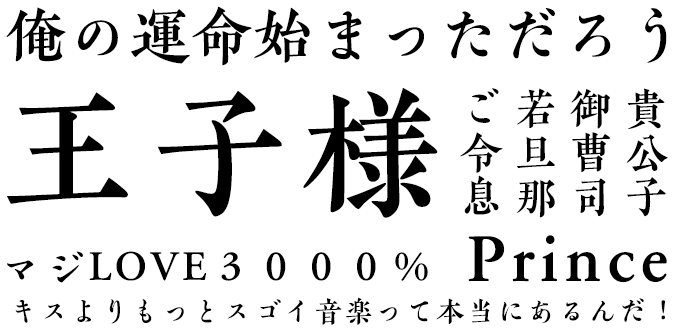
使用フォント:DSあかり
格式高い西洋のプリンスさまを推すのにぴったりのフォント
「プリンス」に合うフォント 金魚ランタン
金魚ランタン 【ヤマナカデザインワークス】
「プリンス」に合うフォント 金魚ランタン
ブラックレター体を日本語の文字として解釈しなおして設計した日本語フォント。欧文・数字は日本語での解釈を元に再設計しているので、本来のブラックレター体とはまた違った印象となっています。強く鋭い印象を持たせたいとき、世界観を強調したい時に是非お使いください。
華麗で美しい書体だからこそ、推しのプリンスさまに使ってほしい!
「プリンス」に合うフォント ロマン雪
ロマン雪 【ダイナフォント】
「プリンス」に合うフォント ロマン雪
独特の字形が大きなインパクトを与えるデザイン書体。大正末期から昭和初期にかけての古典ロマンの雰囲気を再現した書体です。
乙女ちっくな雰囲気がプリンスを推すのにぴったりの明朝体
「プリンス」に合うフォント 恋みんちょう
恋みんちょう 【かに沢のりお】
「プリンス」に合うフォント 恋みんちょう
乙女ちっくでちょっと懐かしい雰囲気、ところどころにハートを散りばめた手作りの明朝体フォントです。
プリンスの華麗な雰囲気をまとったデザインフォント
「プリンス」に合うフォント DF麗雅宋
DF麗雅宋 【ダイナフォント】
「プリンス」に合うフォント DF麗雅宋
明朝体のストロークをより美しく、そして特徴的にアレンジし華麗な雰囲気を演出したロマン風書体です。
王子様のキラメキを感じさせる花文字のような装飾が魅力的な書体
「プリンス」に合うフォント DF優雅宋 W7
DF優雅宋 W7 【ダイナフォント】
「プリンス」に合うフォント DF優雅宋 W7
ストロークの先端と末端に欧文書体の花文字のような装飾が施されているのが特徴的な書体。この特徴が古典的な洋風感を引き出します。
その名の通りエレガント!プリンス様のためのフォント
「プリンス」に合うフォント HGえれがんと平成明朝体W3
HGえれがんと平成明朝体W3 【リコー】
「プリンス」に合うフォント HGえれがんと平成明朝体W3
仮名文字のクルンとした丸いアクセントが楽しい印象を与えてくれる明朝体。ロマンチックでキュート、きゅんとくるセリフやタイトルに最適なデザインです。
落ち着きや安定感がプリンスにぴったりのエジプシャン書体
「プリンス」に合うフォント AFSセリフゴシック04E
AFSセリフゴシック04E 【フォントユーコム】
「プリンス」に合うフォント AFSセリフゴシック04E
欧文のエジプシャン書体に近いデザイン。どっしりと足のセリフは腰の据わった安定したデザインで落ち着きや安定感を与えます。キャプションなど短い解説やロゴなどに応用ください。
ロマン感溢れるデザインがプリンスっぽさを演出する明朝体
「プリンス」に合うフォント AR浪漫明朝体U
AR浪漫明朝体U 【アーフィック】
「プリンス」に合うフォント AR浪漫明朝体U
大正浪漫を彷彿させる明朝系の書体。タイトルや見出しに最適です。
キラキラした王子そのもの!
「プリンス」に合うフォント TA-ドラミン
TA-ドラミン 【FONT1000】
「プリンス」に合うフォント TA-ドラミン
文字にダイヤ形をあしらった、まさにキラキラなプリンスのためのようなフォント。太さもあるので、見出しやロゴにもピッタリです。
格式高いエレガントなプリンスに!
「プリンス」に合うフォント KOさおとめ金陵
KOさおとめ金陵 【欣喜堂】
「プリンス」に合うフォント KOさおとめ金陵
硬質で優雅な明朝体は、エレガントなプリンスを創造させます。本文にも見出しにも使える美しい書体です。
儚いプリンスは耽美の代名詞
「プリンス」に合うフォント DF金文体 StdN
DF金文体 StdN 【ダイナフォント】
「プリンス」に合うフォント DF金文体 StdN
線の細さが美少年プリンスを想像させます。アジアンな王子様にもよく合います。思わずうっとりとするフォントです。
現代のプリンス系アイドルにピッタリのクールなデザイン書体
「プリンス」に合うフォント DF綜藝体
DF綜藝体 【ダイナフォント】
「プリンス」に合うフォント DF綜藝体
通常のゴシック体よりも太く正方な字形を採用し、1文字の中に生じる余白部分を均等化、また、まっすぐ伸びた線の曲がりやハネの先端部分をややカーブさせる事で独特のポップさが生まれたデザイン書体です。
可愛いプリンス様にぴったりのカジュアルなデザイン書体
「プリンス」に合うフォント HT Neon
パンダベーカリー 【鈴木メモ】
「プリンス」に合うフォント HT Neon
2018年秋の発売以来、SNSでも話題の大人気のフォントです。手描きのリズムを活かした、カジュアルで太めの日本語フォントです。
めんそーれ!青い海と憩うよ、プリンス
「プリンス」に合うフォント 横丁&鍛所 あまからフォント
横丁&鍛所 あまからフォント 【六葉情報】
「プリンス」に合うフォント 横丁&鍛所 あまからフォント
プリンスといえば、太い筆文字でやや柔らかい雰囲気のフォントが先に浮かびました。横丁&鍛所 あまからフォント はそのようなプリンスの雰囲気にピッタリなフォントだと思い、選びました。
イバラが似合うのは姫だけじゃない
「プリンス」に合うフォント HT Neon
MdN_Initial 【MdN DESIGN】
「プリンス」に合うフォント HT Neon
イバラを連想させるデザインがKing & Prince どちらにも相応しい上品なフォント、略してキンプリフォントです。
由緒正しい王子様には必須!
「プリンス」に合うフォント HT Neon
Agincourt™ Com 【ITC】
「プリンス」に合うフォント HT Neon
紋章にも使われていそうなカリグラフィーフォント。格調高いプリンスの雰囲気です。
正統派プリンスは控えめでも目立つ
「プリンス」に合うフォント HT Neon
Snell Roundhand® Std Black 【Linotype】
「プリンス」に合うフォント HT Neon
オーソドックスなスクリプト(筆記体)フォント。スタンダードなデザインが上品さと聡明さを引き立てます。